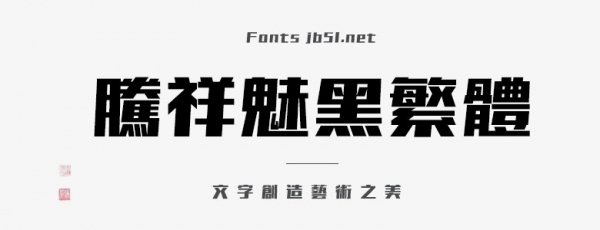
騰祥魅黑繁體是一款不錯的藝術(shù)字體,由騰祥字庫出品,字形結(jié)構(gòu)扁方,橫豎筆畫粗細比例適度、所有豎筆及撇捺筆畫均呈右傾斜式,適合應(yīng)用于藝術(shù)設(shè)計、平面宣傳設(shè)計、網(wǎng)頁設(shè)計,書法字帖等領(lǐng)域,需要的朋友可以前來本站下載。
魅黑是一款富于變化的美術(shù)類黑體。魅黑是在潮黑的風格特征基礎(chǔ)上設(shè)計而成。字形結(jié)構(gòu)扁方,橫豎筆畫粗細比例適度、所有豎筆及撇捺筆畫均呈右傾斜式,為了空間的布局,每個筆畫的傾斜角度由左至右形成梯度,使整個字看起來呈梯形,筆畫雖斜但字形穩(wěn)當。